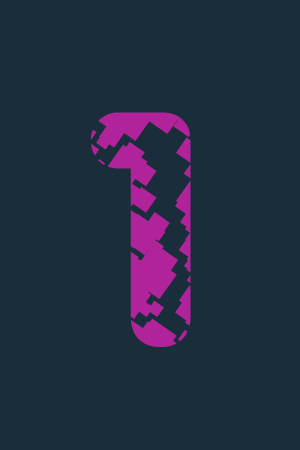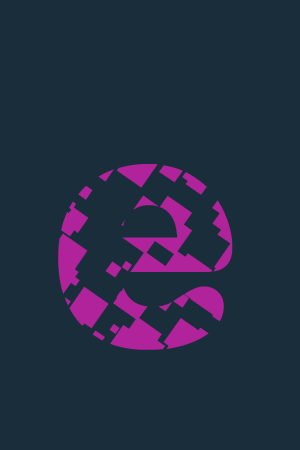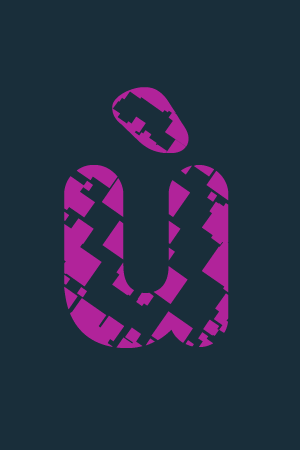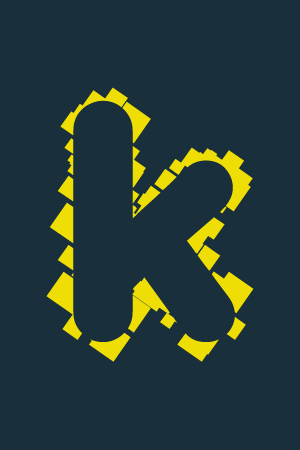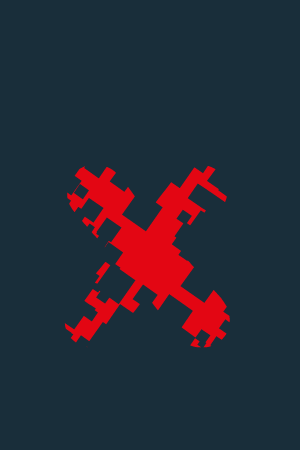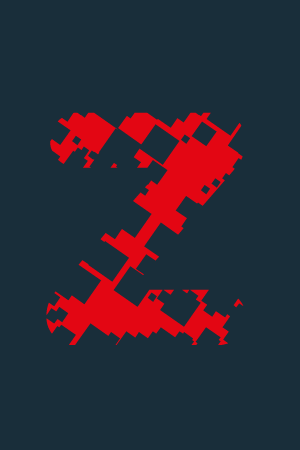
Font Quebrada, rota y destrozada
Lerótica extra bold typeface. Extended character setÚltimamente estoy muy interesado, hablando de diseño tipográfico, en la aplicación de las matemáticas en el estudio de proporciones del desarrollo de una tipografía. Esta fuente Quebrada es un experimento de  deconstrucción libre y distorsión con lineas quebradas de mi último proyecto tipográfico basado en las secuencias de Fibonacci y Lucas. Próximamente editaré esta nueva fuente y explicaré los fundamentos de las proporciones matemáticas aplicado al diseño de fuentes tipográficas.
La fuente dispone de 443 glifos, se puede usar en cualquiera de los idiomas européos y el kerning está bien definido.
Encontrarás de utilidad esta fuente para trabajos de cartelería o diseño de posters, también para títulos en publicaciones o para cualquier diseño donde el estilo de la tipografía consideres que es adecuado, por causa de la deformación, la legibilidad en pequeños tamaños queda muy comprometida.